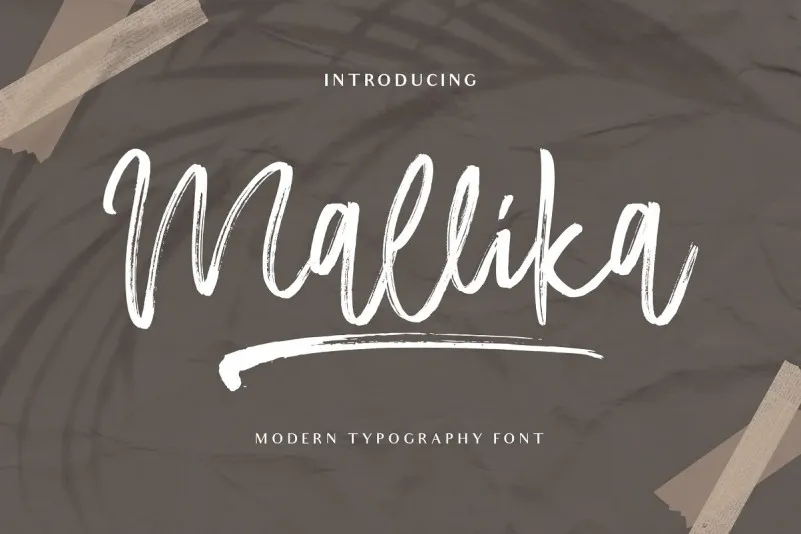
Mallika Brush Font – Download Grátis
A fonte “Mallika Brush Font” é uma beleza elaborada à mão criada por Fontherapy para quem busca expressar individualidade em projetos visuais. Com um estilo elegante e atraente, esta tipografia de grafismo suave pode ser usada não apenas para criar logotipos ou templates, mas também para dar vida a cartas de convite, blogs, marcas, livros, revistas, anúncios, sobras, design de marca e muito mais. Seja em um projeto personalizado ou uma campanha publicitária, “Mallika Brush Font” trará profissionalismo e charme à sua arte digitais. Este script font foi criado para aqueles que buscam algo refinado e único, certamente capaz de destacar seus trabalhos. Não importa qual área você esteja atuando — desde a design gráfica até o marketing digital — esta fonte oferece um toque especial e personalizado para seu projeto.